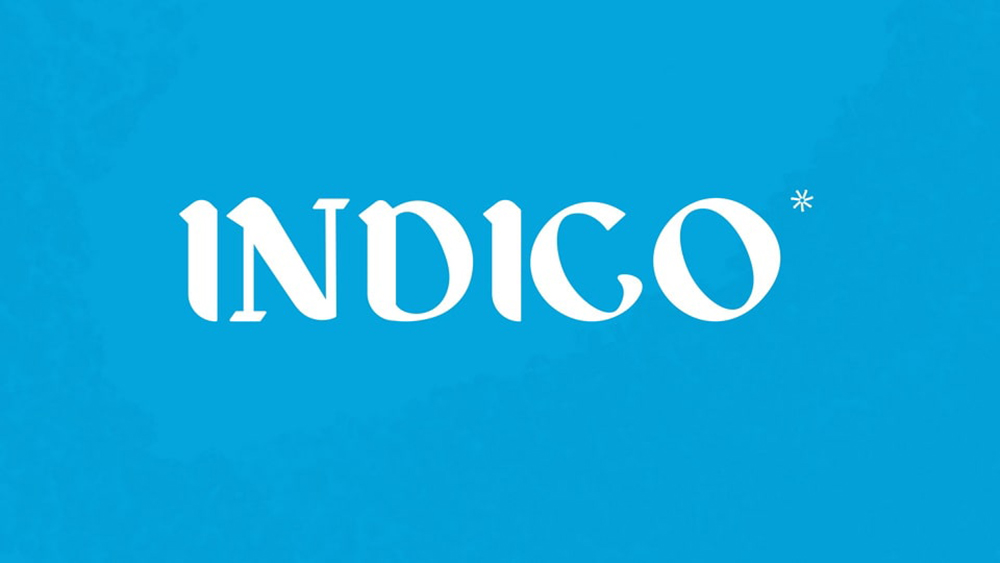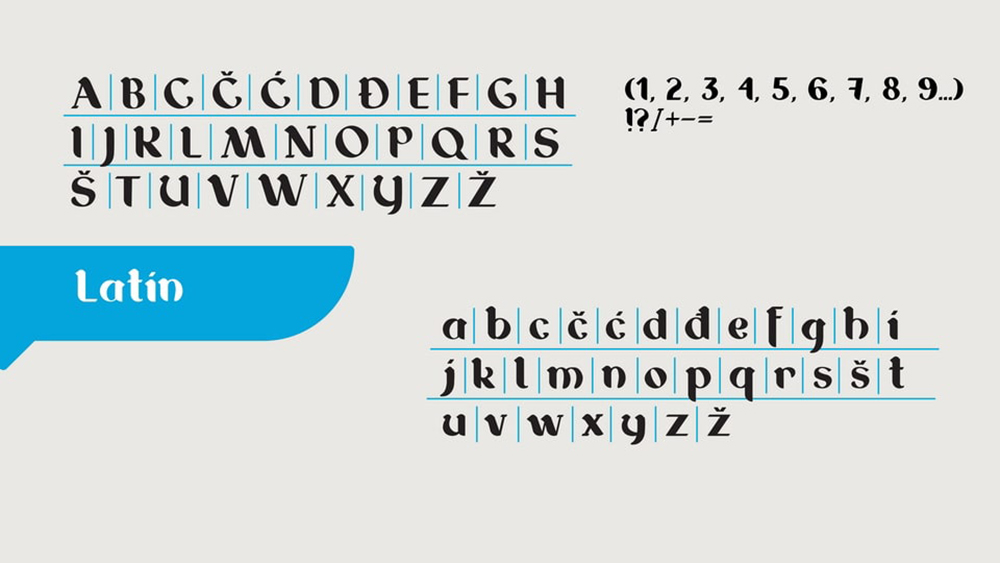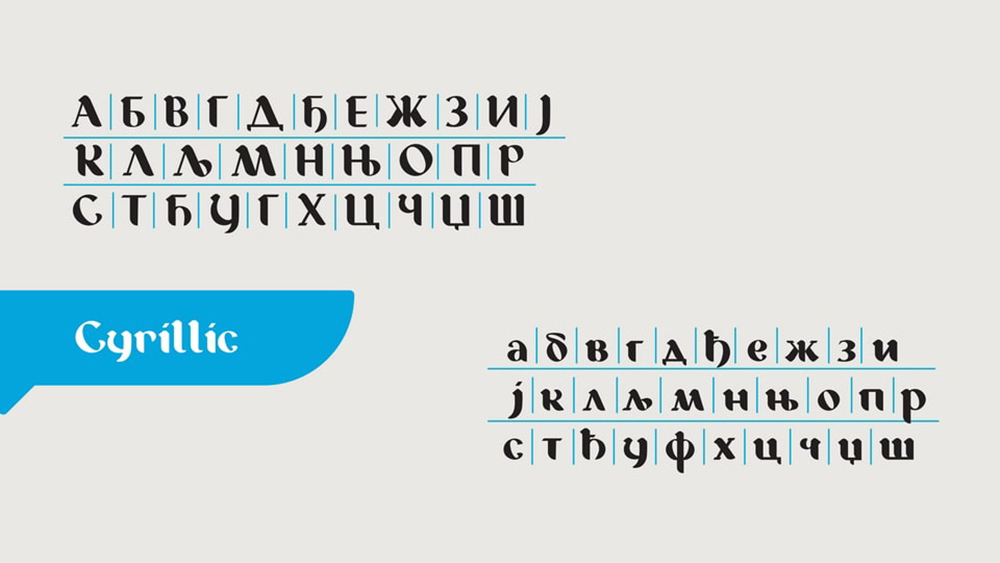
فونت پرمیوم و انگلیسی Indico Font فونتی است که ظرافت مرموز حروف گوتیک را با پیچیدگی بیزمان طراحی آنتیکوا به طور یکپارچه در هم میآمیزد. این فونت به تاریخ غنی نسخههای خطی قرون وسطی ادای احترام میکند و روح خوشنویسی گوتیک را در قالبی معاصر و همهکاره در بر میگیرد. فونت ایندیکو دارای حروفی با سریفهای تیز و زاویهدار و جزئیات متمایز یادآور معماری گوتیک است. تلفیق عناصر گوتیک با تأثیرات آنتیکوا منجر به یک تجربه تایپوگرافی منحصر به فرد و جذاب میشود که از مرزهای سنتی فراتر میرود. فونت ایندیکو که برای پروژههایی که به دنبال لمس رمز و راز تاریخی هستند، ایدهآل است، حس درام و پیچیدگی را به طرحبندیهای سرمقاله، برندسازی و تلاشهای خلاقانه میآورد. اشاره آن به سنت گوتیک-آنتیکوا، فونتی همهکاره را در اختیار طراحان قرار میدهد که حال و هوایی از پالایش بیزمان به هر ترکیب تایپوگرافی میبخشد.